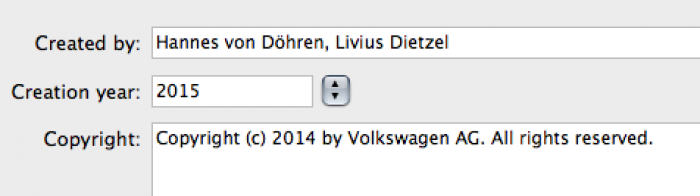
Neuer Corporate Font bei Volkswagen im Anmarsch?
Sieht gut aus. Wirkt viell. in diesem Zusammenhang etwas behäbig? Und etwas, nun ja, unspezifisch? Ob sie dazu beiträgt, das Markenbild zu schärfen?
Die Zurichtung hat noch Potential …
So, jetzt ist es amtlich:
Volkswagen führt derzeit eine neue Hausschrift ein. Gleichwohl ein evolutionärer Schritt, wird der Umstellungsprozess aufgrund der Vielzahl an analogen und digitalen Anwendungen viele Monate in Anspruch nehmen. Der Aufwand lohnt, davon sind die Markenverantwortlichen bei Volkswagen jedenfalls überzeugt, sorgt das neue Schriftenkonzept doch für eine „360° Brand Experience“, wie es in der gestern veröffentlichten Pressemeldung im besten Marketing-Sprech heißt. Im Design Tagebuch wird die neue Schrift mit exklusivem Bildmaterial vorgestellt.